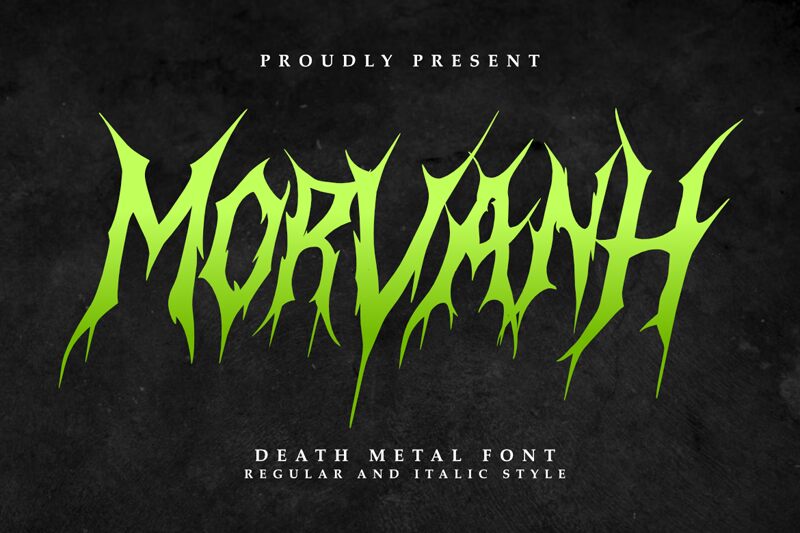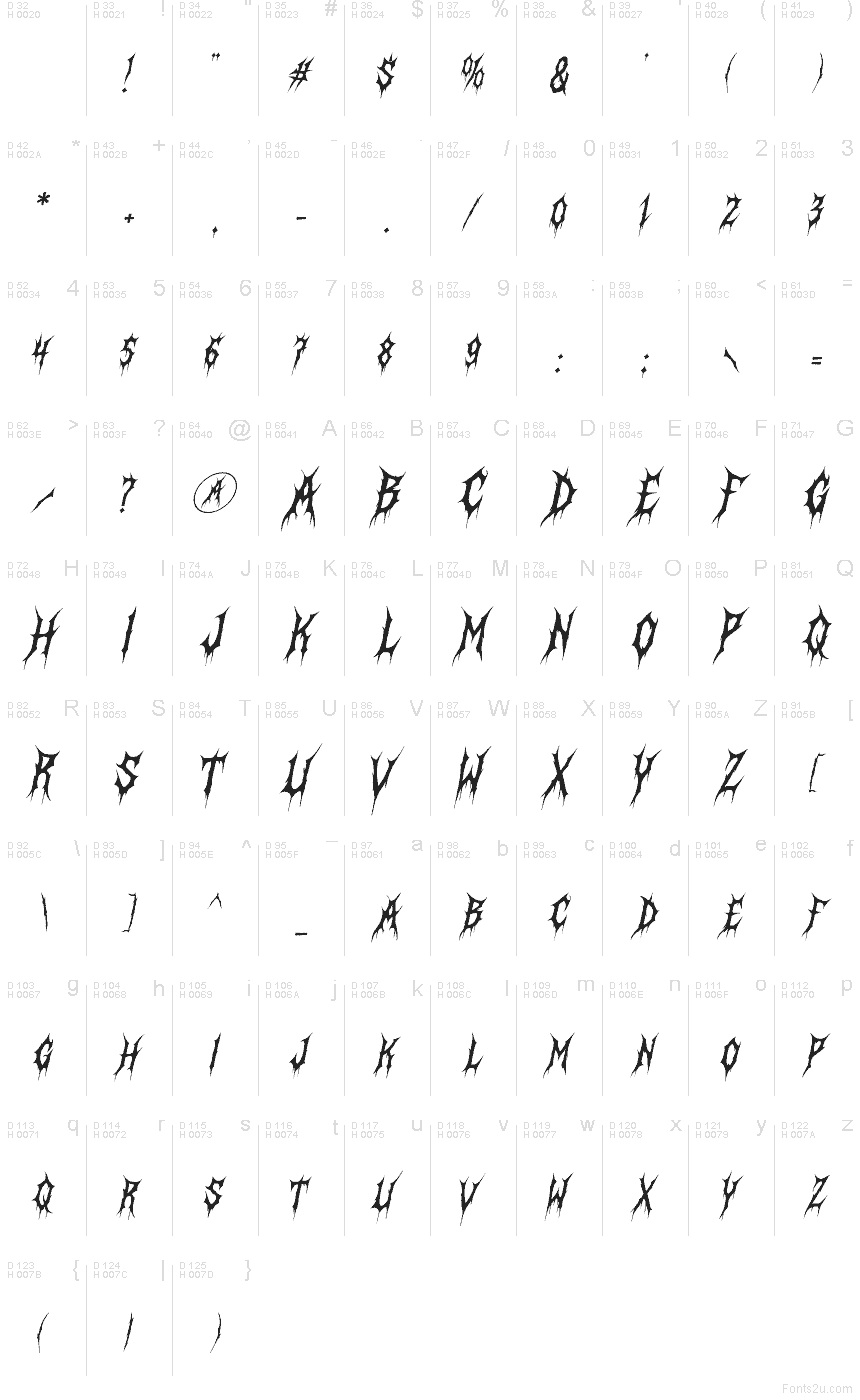
Morvanh Italic
La police Morvanh Italic de Masyafi Studio est une typographie gothique gratuite de type display qui se distingue par ses traits tranchants et ciselés, donnant aux lettres un rythme fragmenté et acéré. Les formes s'effilent en pointes étroites, tandis que son inclinaison insuffle un élan dynamique à l'ensemble, sans jamais perdre son caractère sombre et anguleux.
Morvanh Italic est une police gratuite idéale pour les logos de groupes, les titres d'affiches, les pochettes d'albums, les jaquettes de jeux ou les projets de branding orientés horreur où ce style gothique agressif est nécessaire. Elle convient également parfaitement aux designs de tatouages, aux flyers d'événements et aux titres décoratifs qui ont besoin de punch sans fioritures inutiles.